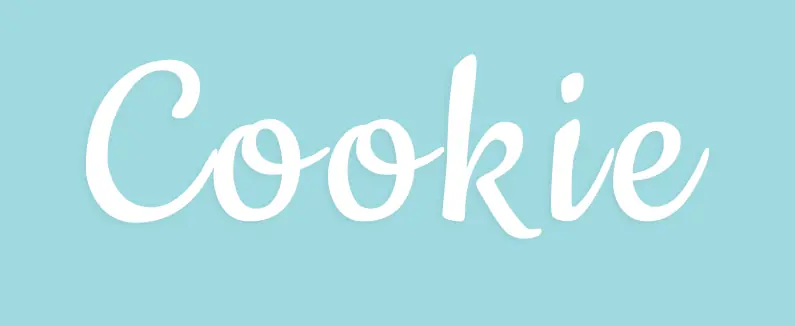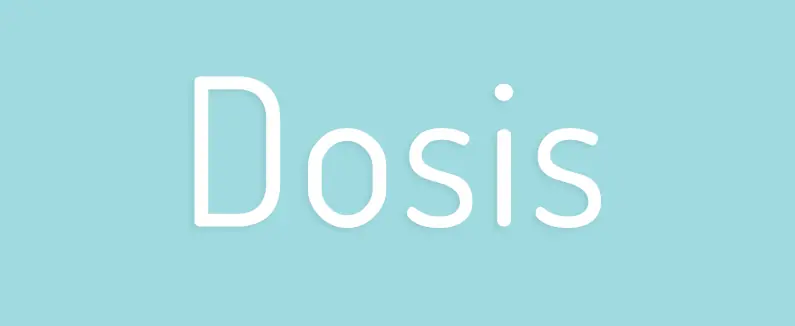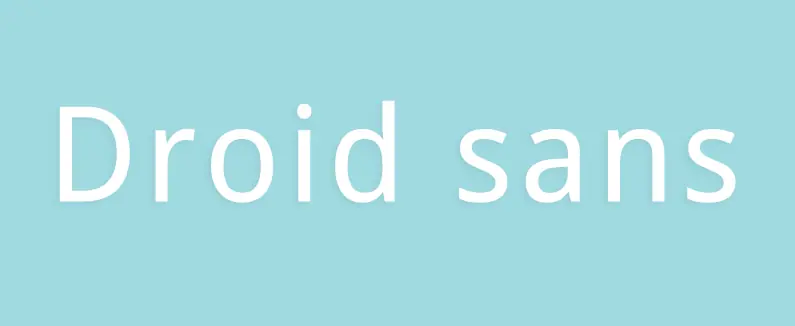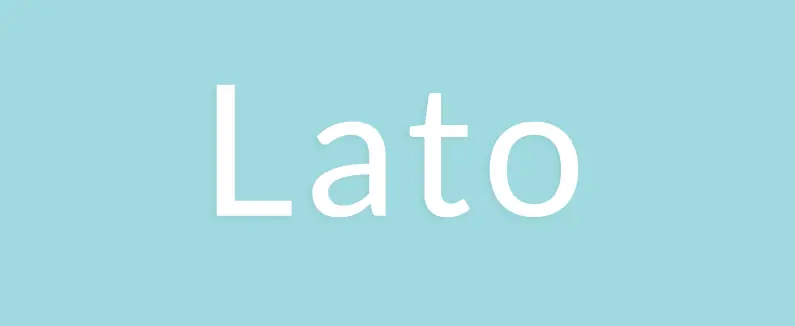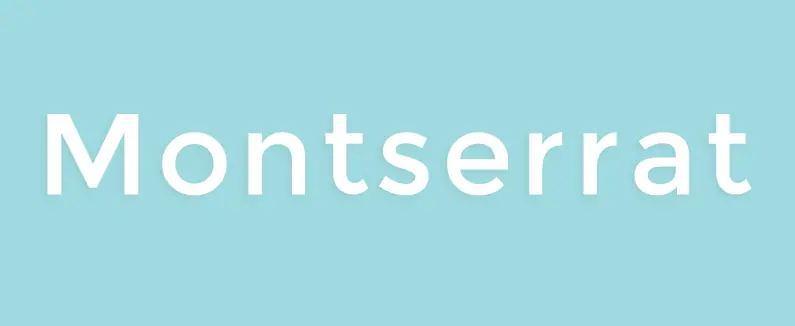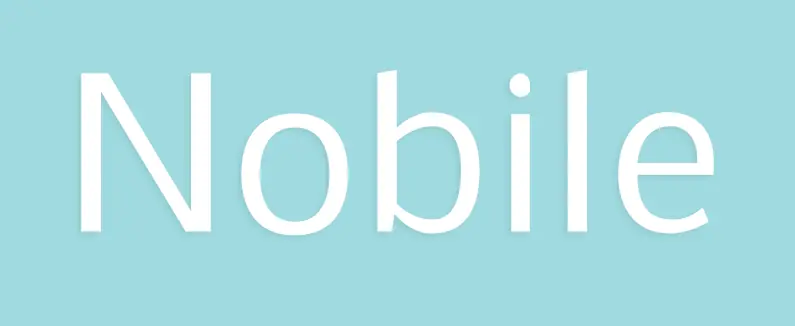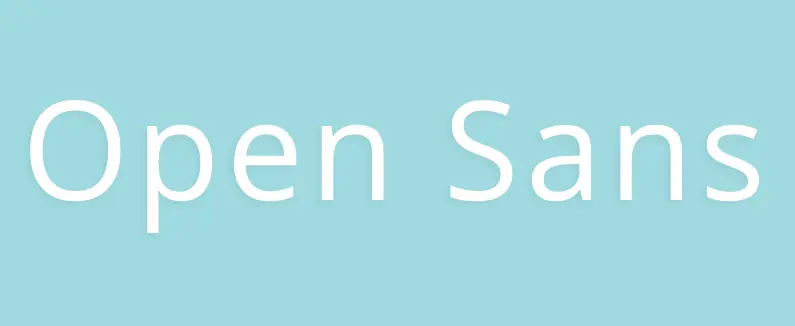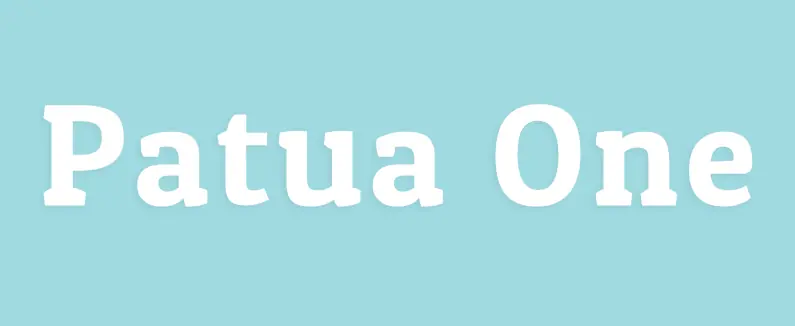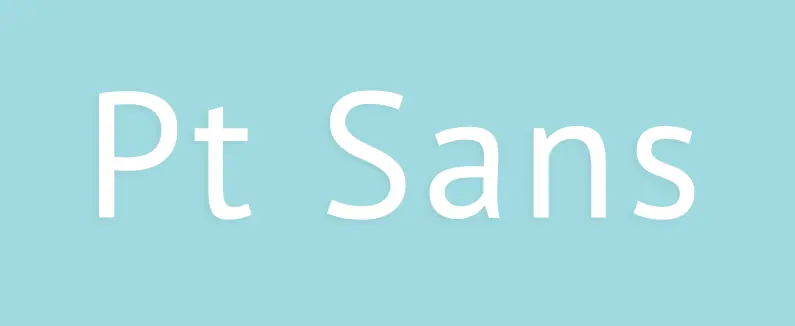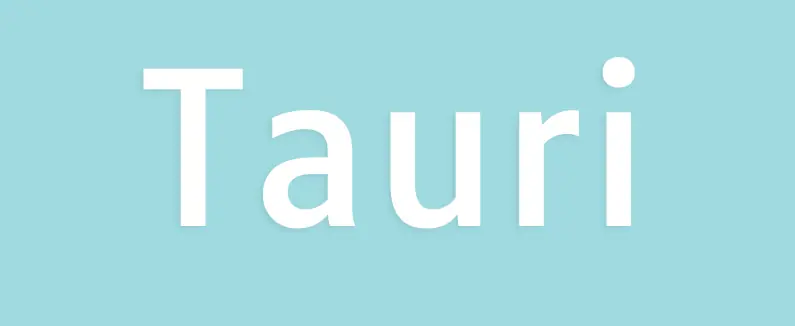
Cabin
Tipografía inspirada en las de los maestros tipógrafos Eric Gill o Edward Johnston, Cabin es una fuente sin serifa moderna, aunque mantiene sus raíces clásicas. Viene en 8 estilos diferentes.
Lato
Lato es una tipografía sin serifa diseñada en el verano de 2012 por el diseñador polaco Łukasz Dziedzic (“Lato” significa verano en polaco). En diciembre de ese mismo año fue publicada bajo licencia open-source para que todos podamos disfrutarla.
Open Sans
Diseñada por Steve Matteson, director de tipografía de Ascender Corp, Open Sans fue diseñada para tener una apariencia amable y para ser óptimamente legible tanto en impresión como en web y dispositivos móviles. Es quizás una de las tipografías de Google Fonts más utilizadas, un clásico contemporaneo.
PT Sans
PT Sans fue desarrollada por el proyecto “Public Types of Russian Federation.” La segunda familia del proyecto, PT Serif también está disponible. El principal objetivo del proyecto era ofrecer al pueblo ruso la posibilidad de leer y escribir en su propio idioma con facilidad.
Droid Sans/Serif
Droid Sans es otra tipografía diseñada por Steve Matteson de Ascender Corp. Droid Sans es perfecta para grandes titulares en negrita, mientras que Droid Sans es más adecuada para cuerpo de texto por su gran legibilidad.
Arvo
Preciosa tipografía con serifa optimizada para pantalla e impresión.
Patua One
Diseñada para tamaños pequeños, Patua One luce también en grande. Sus suaves curvas son muy agradables para la vista y mantienen la legibilidad.
Cookie
Cookie está basada en caligrafía con pincel. Siempre podemos necesitar una buena script para un gran titular o para una web con estilo vintage.
Vollkorn
Diseñada por Friedrich Althausen, Vollkorn es una fuente robusta y elegante. Perfecta para tus proyectos más exigentes.
Varela Round
Sus suaves y redondeadas líneas hacen a Varela round perfecta tanto para pequeños como grandes tamaños.
Montserrat
Una de nuestras favoritas. Montserrat queda bien la pongas donde la pongas. Una fuente con personalidad.
Nobile
El amigo Raúl Montero nos recomendaba por Twitter incluir está tipografía tan personal y característica.
Tauri
Tauri es una fuente limpia y muy legible en pantalla que nos recomendaba Alberto Cuadrado .
Dosis
Y otra fuente que nos recomendaba Alberto es Dosis, una tipo estrecha y redondeada, muy agradable para titulares.
Ubuntu
Ubuntu significa en zulú y xhosa: “humanidad hacia otros”. Además, como fuente es chulísima.
Viga
Viga es diferente, tiene personalidad propia y destacará allá donde decidas usarla.
Source Sans pro
Una todo terreno como Open Sans o Pt Sans. Ponla donde quieras, quedará estupenda.